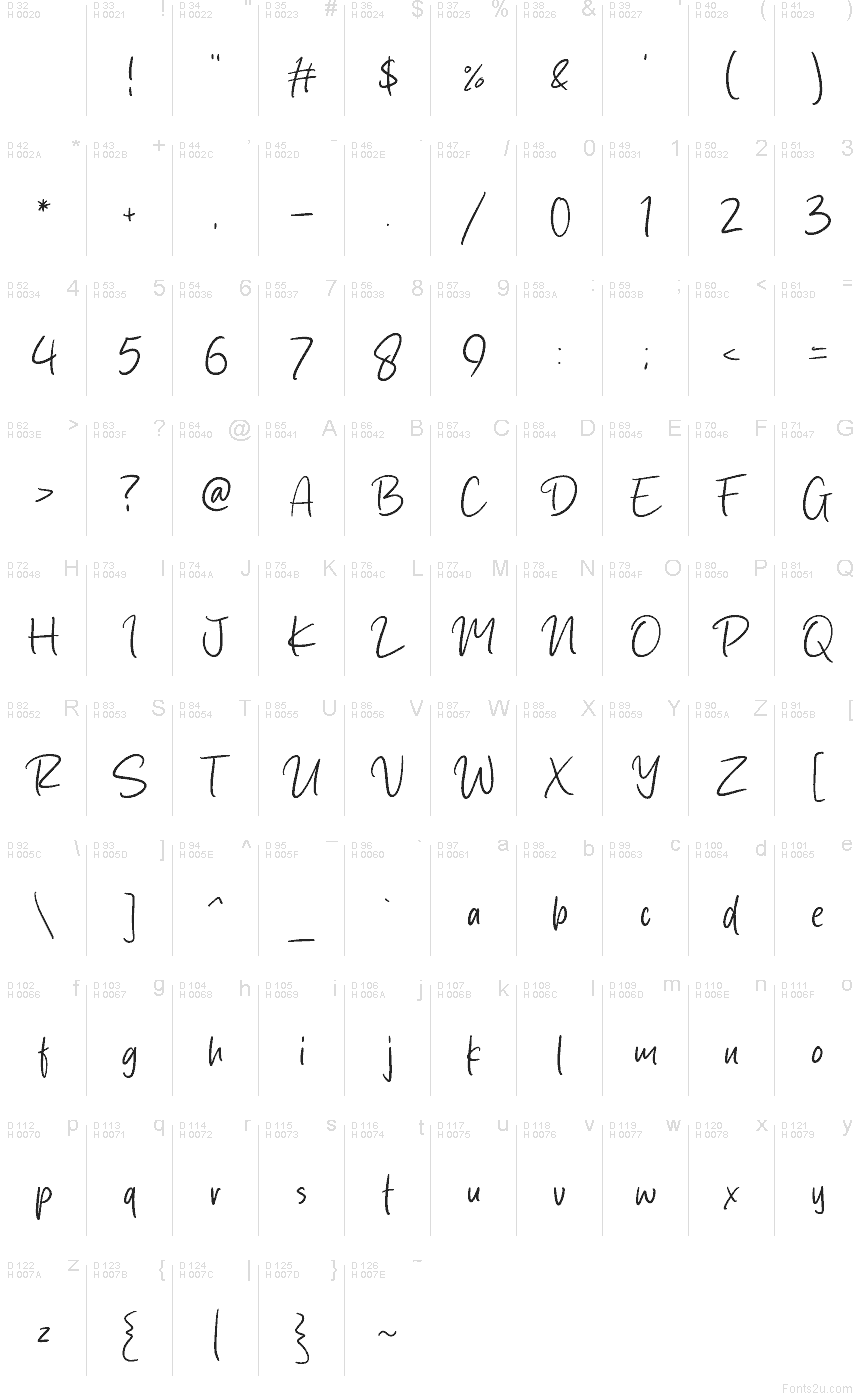
Casual Signature
Casual Signature من MJType هو خط يدوي مجاني مستوحى من الإيقاع السريع وغير المتكلف للملاحظات الشخصية. بفضل بداياته المرتفعة وضرباته النحيفة والمستديرة، يمنح الخط مظهراً خفيفاً وغير رسمي، أقرب إلى التوقيع اليومي العفوي منه إلى الخطوط المنمقة.
هذا يجعله خياراً طبيعياً لتوقيعات الشعارات، وتغليف المنتجات البوتيكية، واقتباسات وسائل التواصل الاجتماعي، وعناوين الدعوات، وبطاقات العلامات التجارية الصغيرة. الإيقاع السلس للضربات يضفي لمسة شخصية على النصوص القصيرة، خاصة في المشاريع التي تحتاج إلى شيء أكثر نعومة وأقل تكلفاً من الخطوط الرسمية.